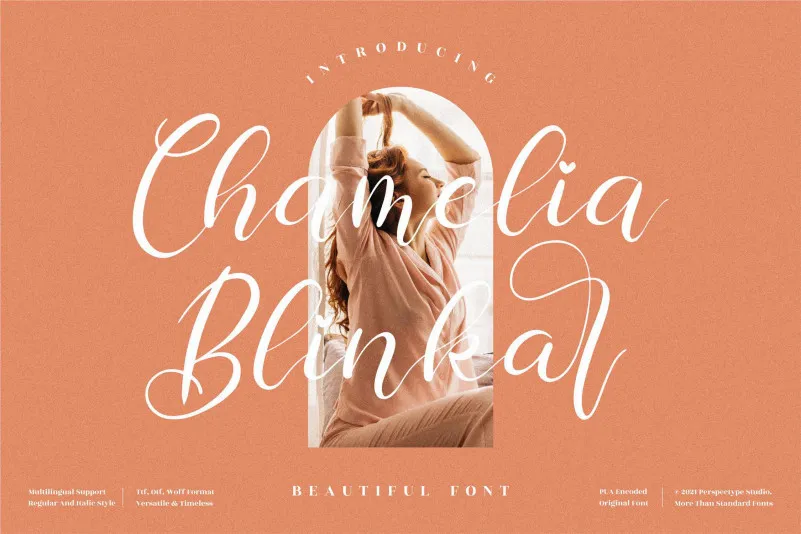
Chamelia Blinkar Font – Download Grátis
Essa é uma fonte feita à mão delicada e elegante, com letras distintas e bem equilibradas que a tornam uma verdadeira obra-prima. Suas características únicas criam um estilo versátil e inovador, perfeito para transformar designões simples em algo singularmente especial. O fato de ser PUA encodado significa que você pode acessar facilmente todos os gílios e swashes, permitindo-lhe explorar infinitamente suas possibilidades criativas. Seja para criações gráficas tradicionais ou experimentações mais audaciosas, Chamelia Blinkar Font será sempre a escolha certa. Adquira-a agora e transforme seus projetos em algo verdadeiramente único.